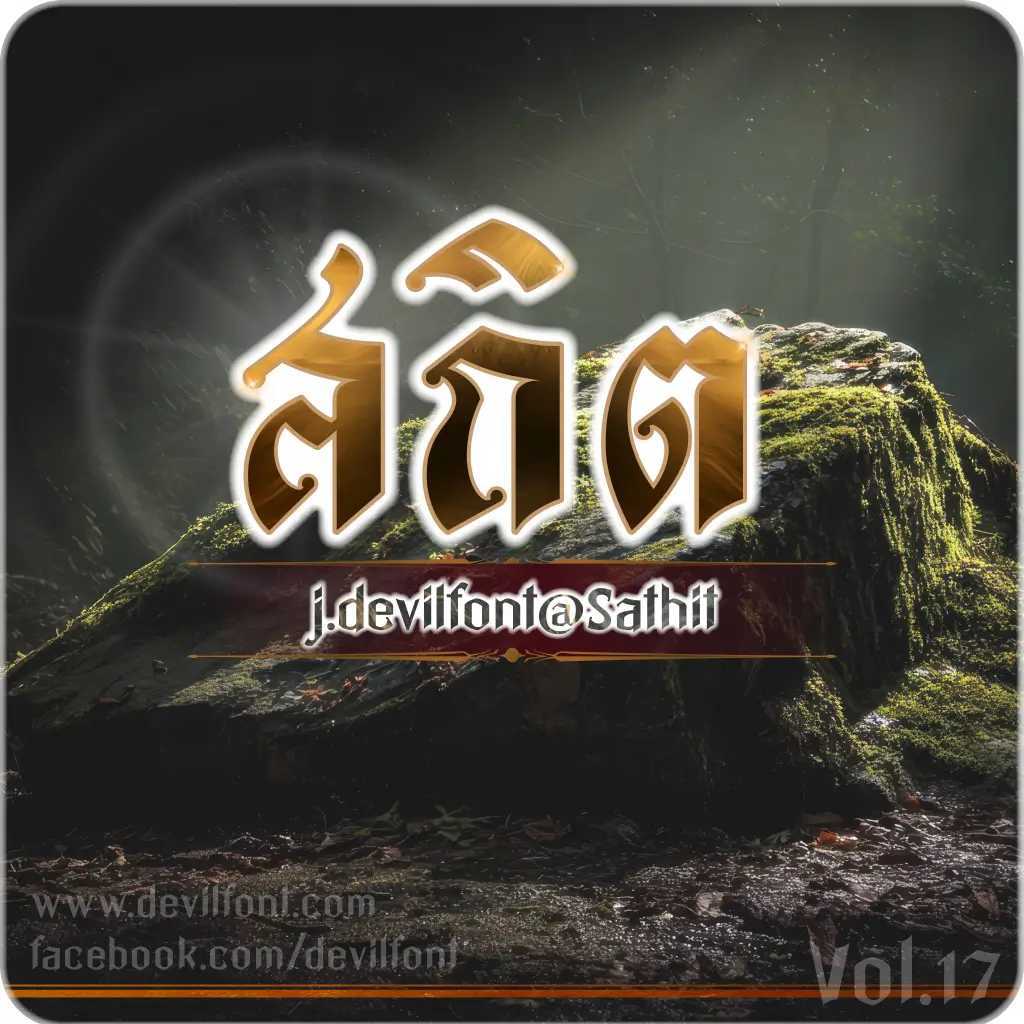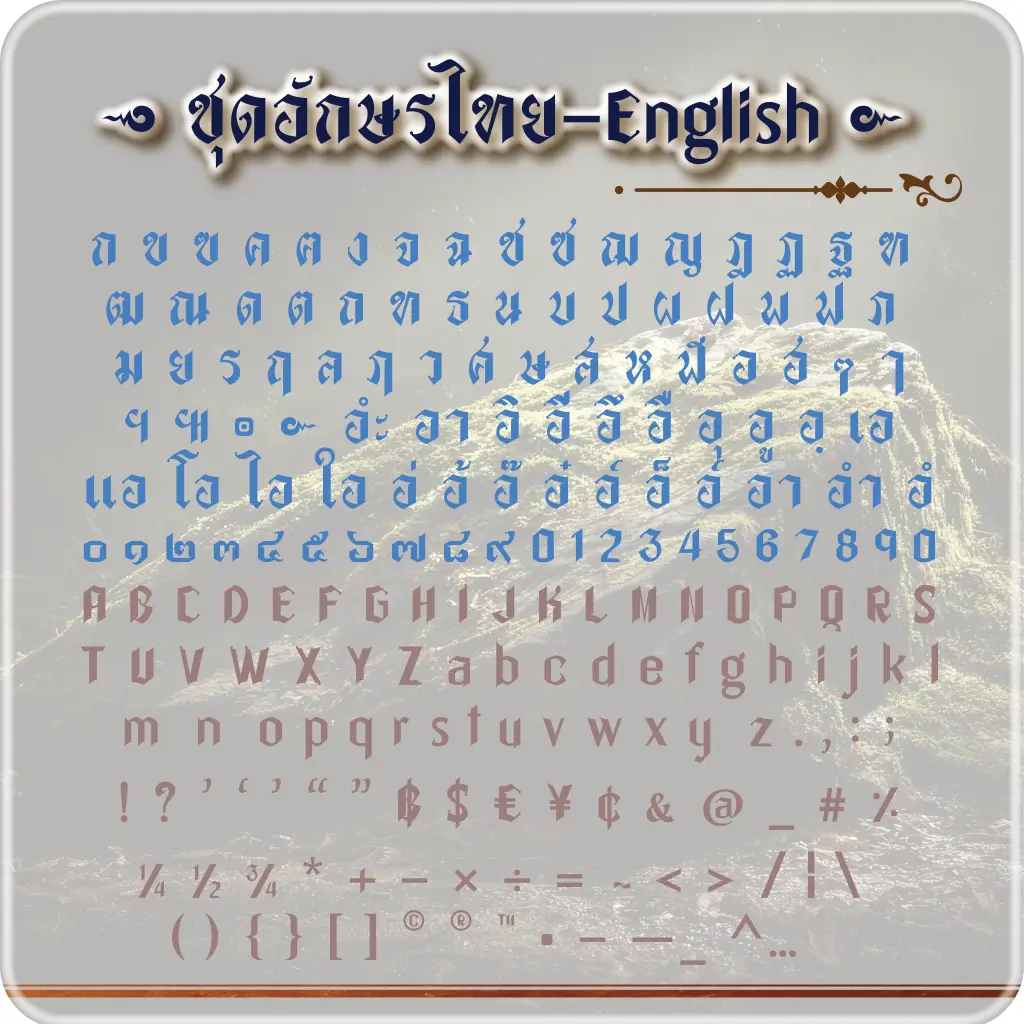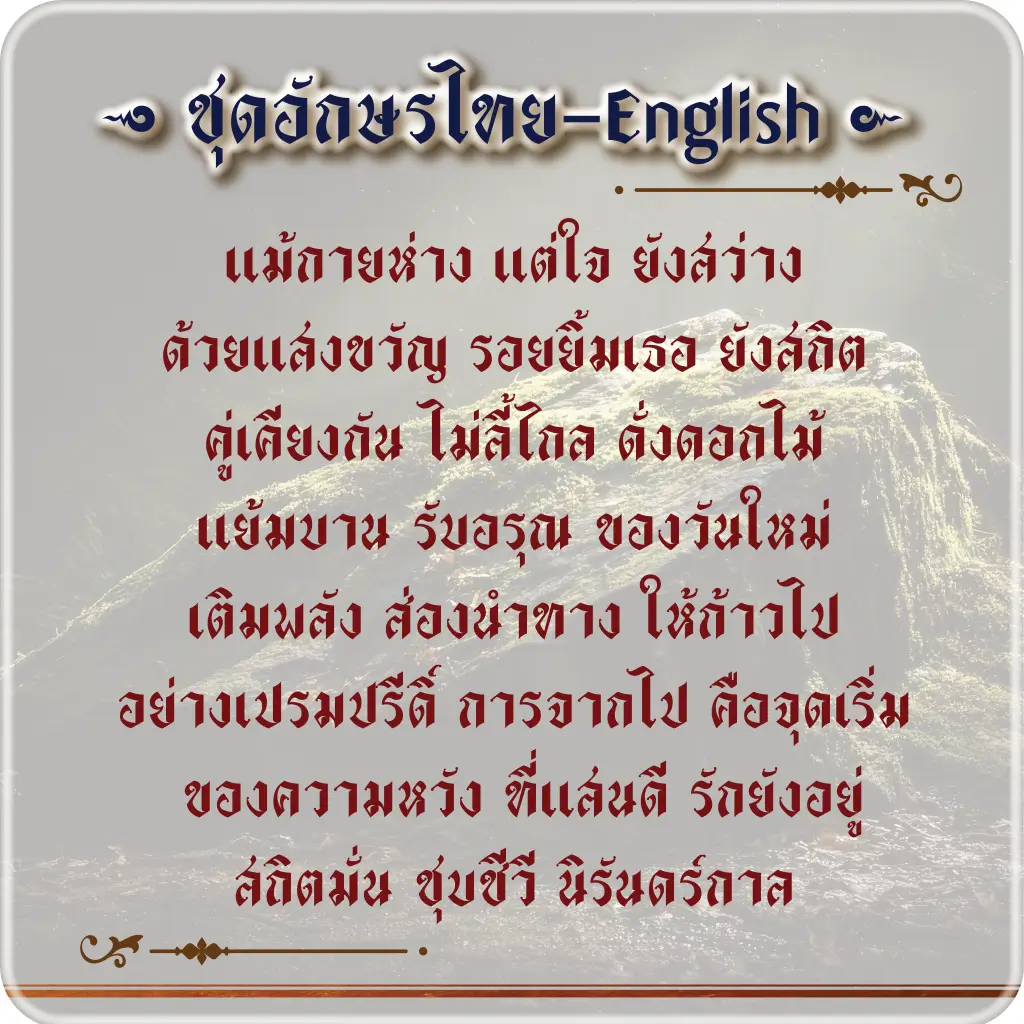
สถิต (j.devilfont@Sathit)
ฟอนต์ สถิต ผลงานฟอนต์ชุดที่ 17 – ลักษณะฟอนต์ไทย พาดหัว งานป้าย งานไม้ งาน cnc บทกลอน ป้ายร้านค้า สายมู ปกนวนิยาย นิตยสาร เทศกาล ศาลเจ้า ของโบราณ โลโก้ สกรีนเสื้อ แสดงงานพิธี สารคดี สื่อโฆษณา แบรนด์สินค้า ความเป็นเอกลักษณ์ไทยโบราณร่วมสมัย
รายละเอียด ฟอนต์สถิต
• ใช้งานด้วย kerning ปรับระยะห่างของชุดอักษรทั้งไทย-อังกฤษ
• ใช้ mark ในการจัด อักษร+สระ+วรรณยุกต์ เพิ่มการไล่ระดับสระ+วรรณยุกต์ อัตโนมัติ
• เพิ่มลูกเล่นที่ โ ใ ไ ที่ยืด-หด และเปลี่ยนรูปในเวลาพิมพ์อัตโนมัติ
• ตัวอักษรมีหาปรับหางสั้นเองเมื่อพิมพ์  สระอิ อี อึ อื  ่   ้   ๊  ๋  ์   ็  ั  ํ
• ตัวอักษรมีหางปรับหางสั้นเองเมื่อพิมพ์ตัวที่คำตัวอักษรที่มีหาง เช่น สี่ปี หาง ส จะไม่ทับกับสระอีบน ป / ป่ป้ป๊ป๋ เปลี่ยนรูปทรง
• เพิ่มวิธีการพิมพ์ โคมูตร ( ๛ ) กด  ฯ147963 ต้องการโคมูตรตัวพิเศษกลับด้าน 147963ฯ
• เพิ่มวิธีการพิมพ์ตัวบาลี ญ ฐ แบบไม่มีเชิง ด้วยการกด ญฯฯ  /  ฐฯฯ  จะได้ตัวที่ไม่มีเชิง
• ตัวอักษรอังกฤษ ก็มีการปรับค่าแก้โค้ดให้ไม่มีหางทับกัน แบบ auto
• ปล. ยังมีลูกเล่นซ่อนอยู่อีก …ฯลฯ แต่ส่วนใหญ่จะเป็นการปรับอัตโนมัติแล้ว
ออกแบบโดย : เจ.ปีศาจฟอนต์